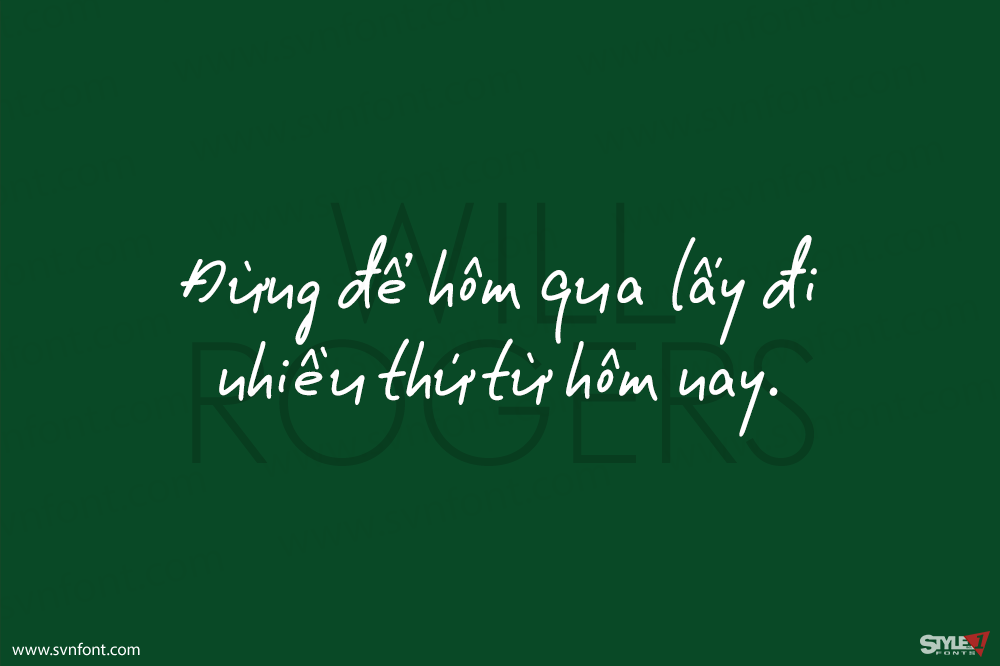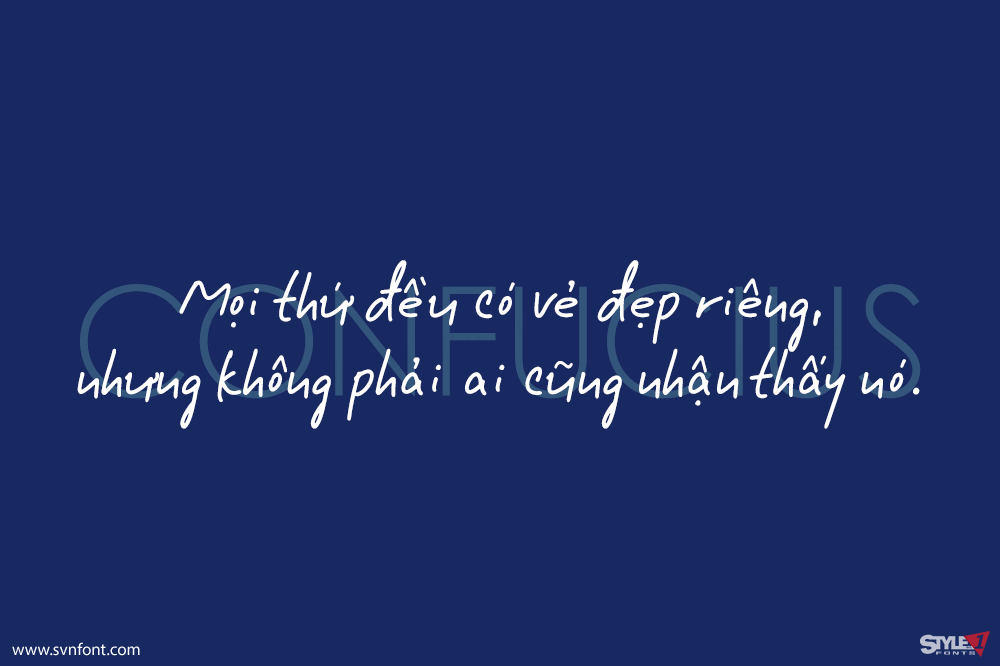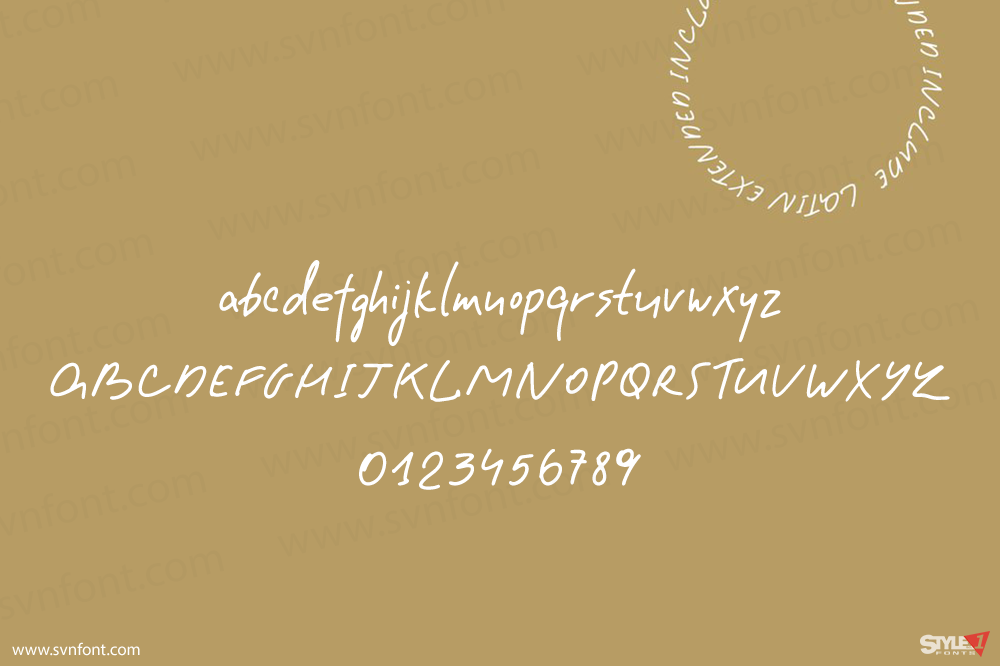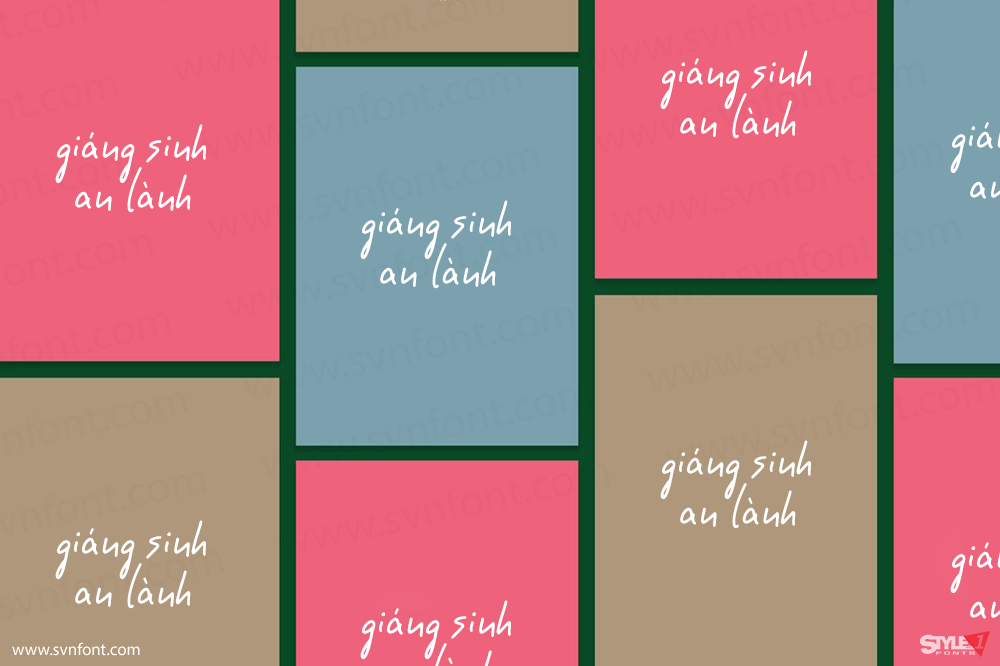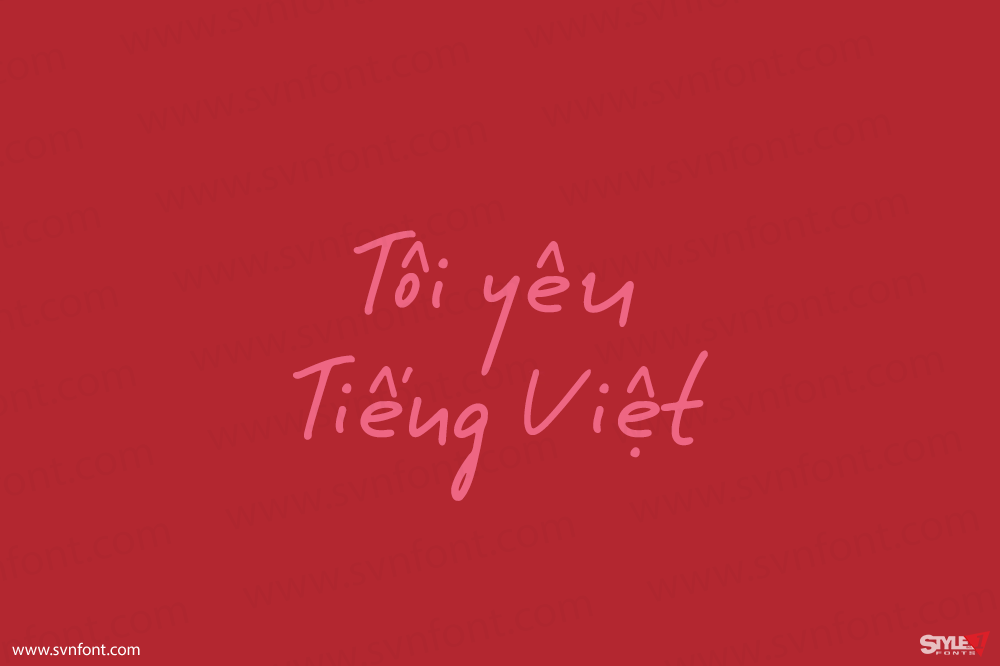
Chào mừng bạn đến với font chữ viết tay lễ hội nhất, SA XMAS MOOD! Font này được tạo ra đặc biệt cho chữ ký Giáng sinh. Nó hoàn hảo cho bưu thiếp, nhãn dán, trích dẫn và ký tên ảnh cho mạng xã hội. Tông màu quyến rũ và thân thiện của font chữ sẽ thêm chút niềm vui đặc biệt vào lời chúc mừng ngày lễ của bạn.
Phong cách viết tay mang đến cho mỗi ký tự một vẻ ngoài độc đáo, làm cho thông điệp của bạn nổi bật. Vậy hãy lan tỏa niềm vui ngày lễ năm nay với SA XMAS MOOD!